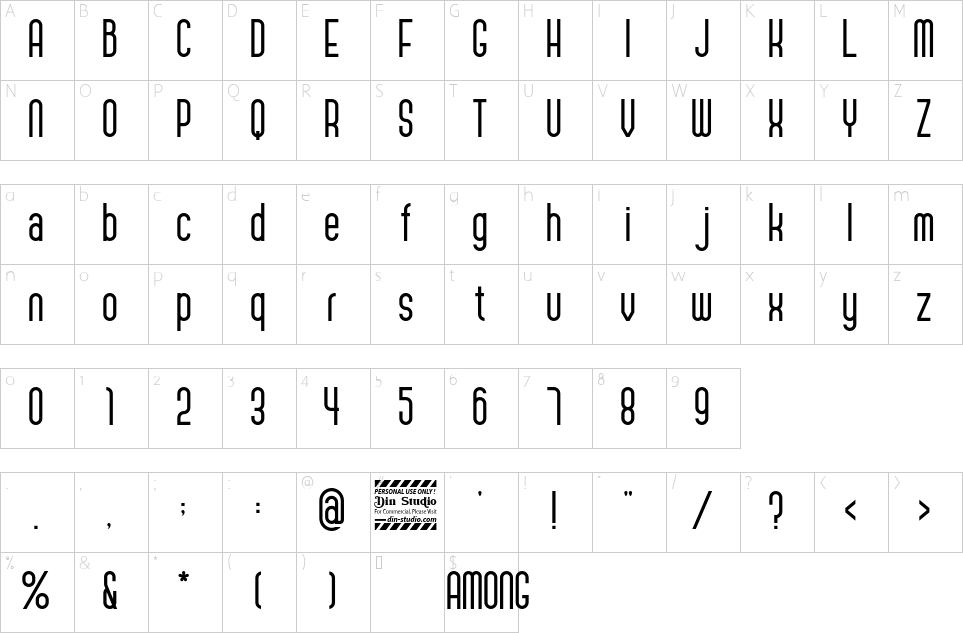
Among Font – Download Grátis
A fonte gratuita Among oferece uma alternativa elegante e versátil para designers e criadores de conteúdo em seu dia a dia. Desenvolvida por Donis Miftahudin, esta fonte já foi baixada 474 vezes. Among é perfeita para aplicativos de design digital, como logos, editoras de texto e até para criação de sites. Suas linhas fluidas e elegantes tornam a Among uma escolha ótima para criar um visual atraente e profissional. Se você está procurando uma fonte bonita e fácil de usar, Among pode ser a opção perfeita para o seu próximo projeto.